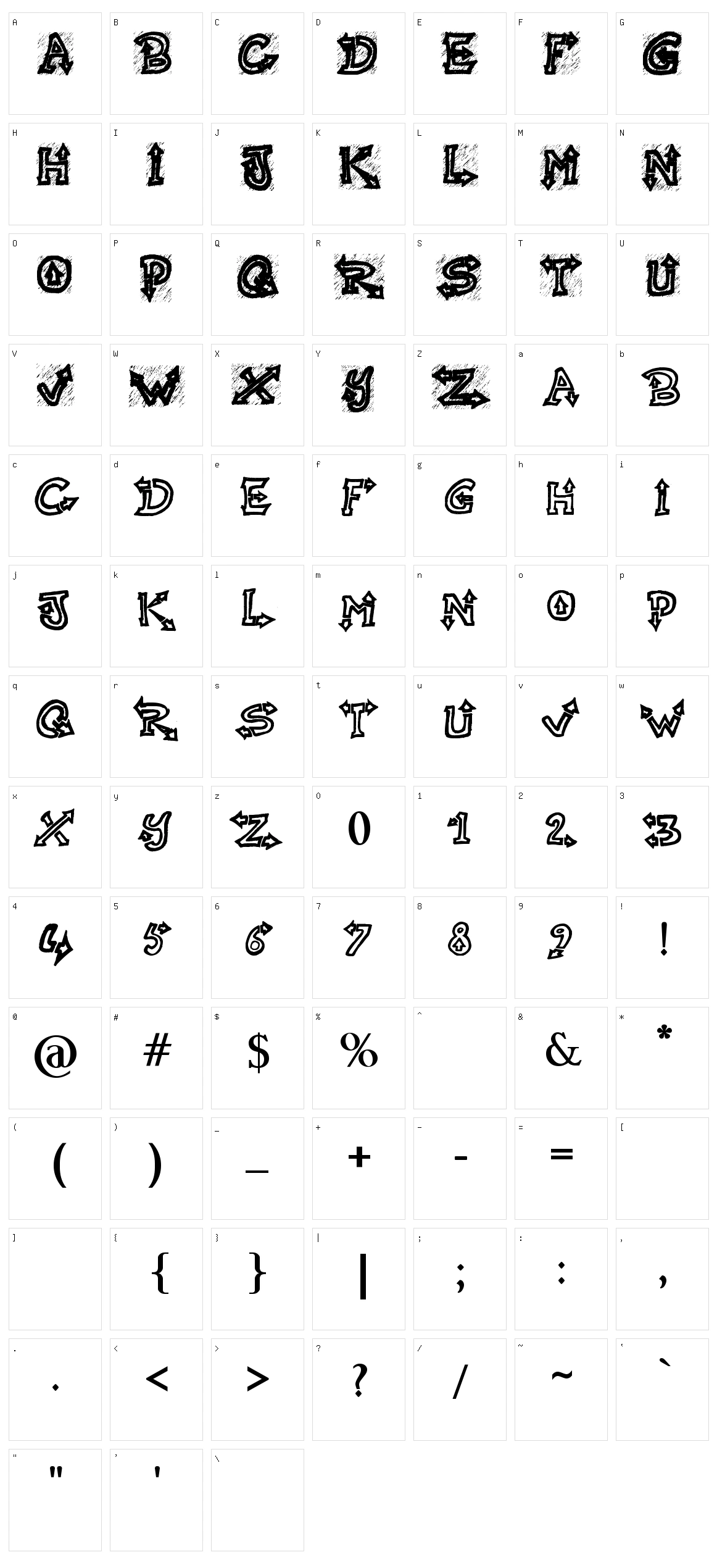
Il s'agit d'une écriture d'abord manuscrite puis scanée et assemblée pour en faire une police pour vos documents,
vos montages, ou autres choses dans le même goût.